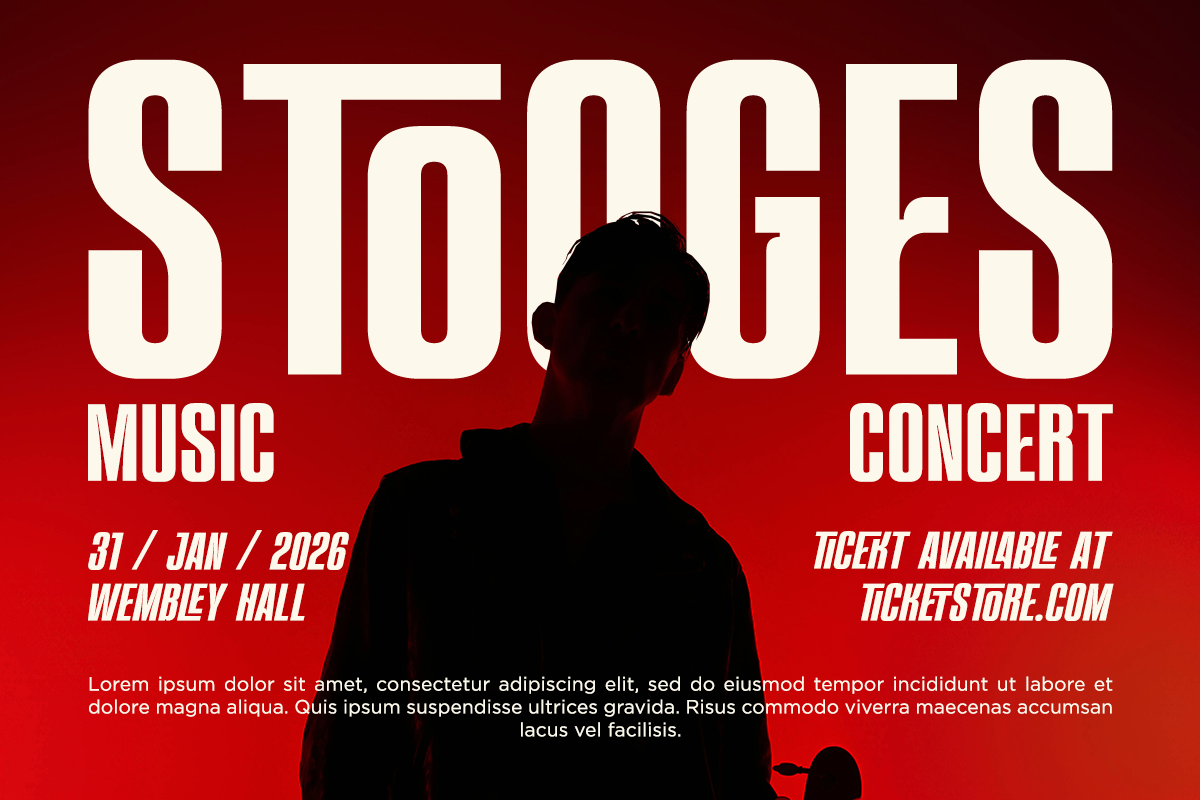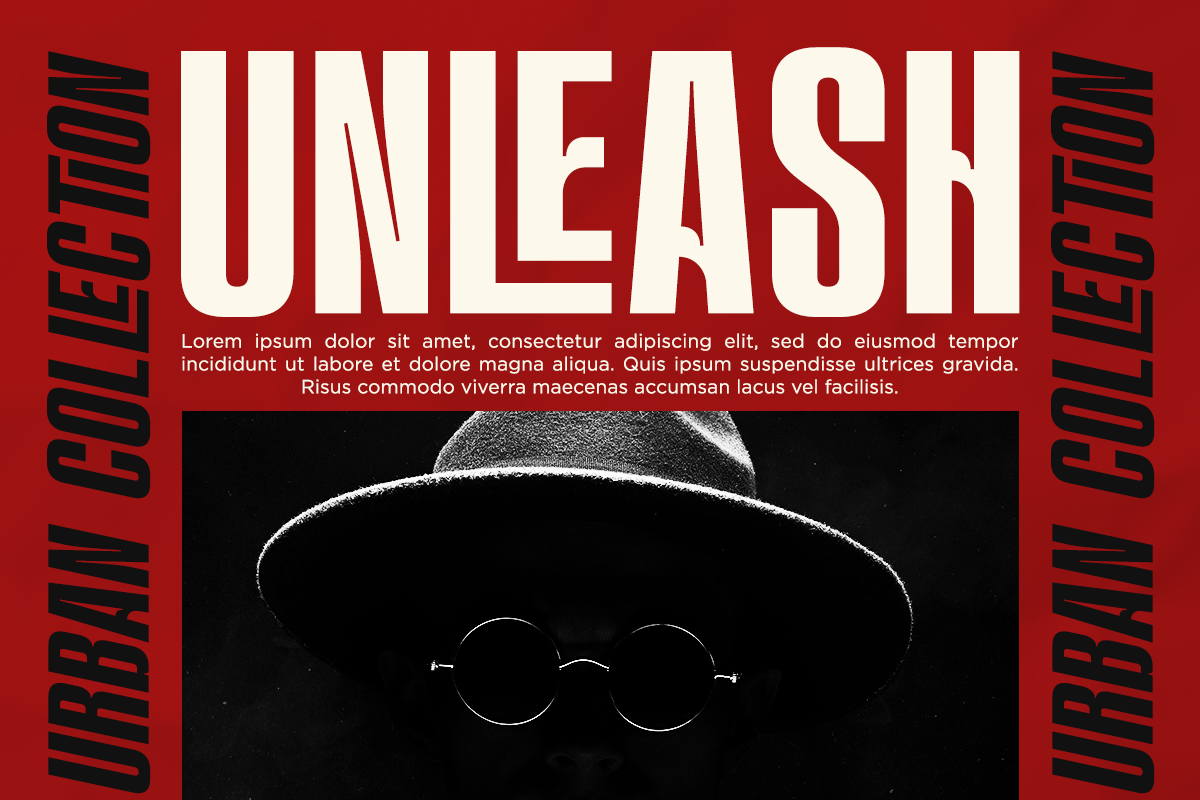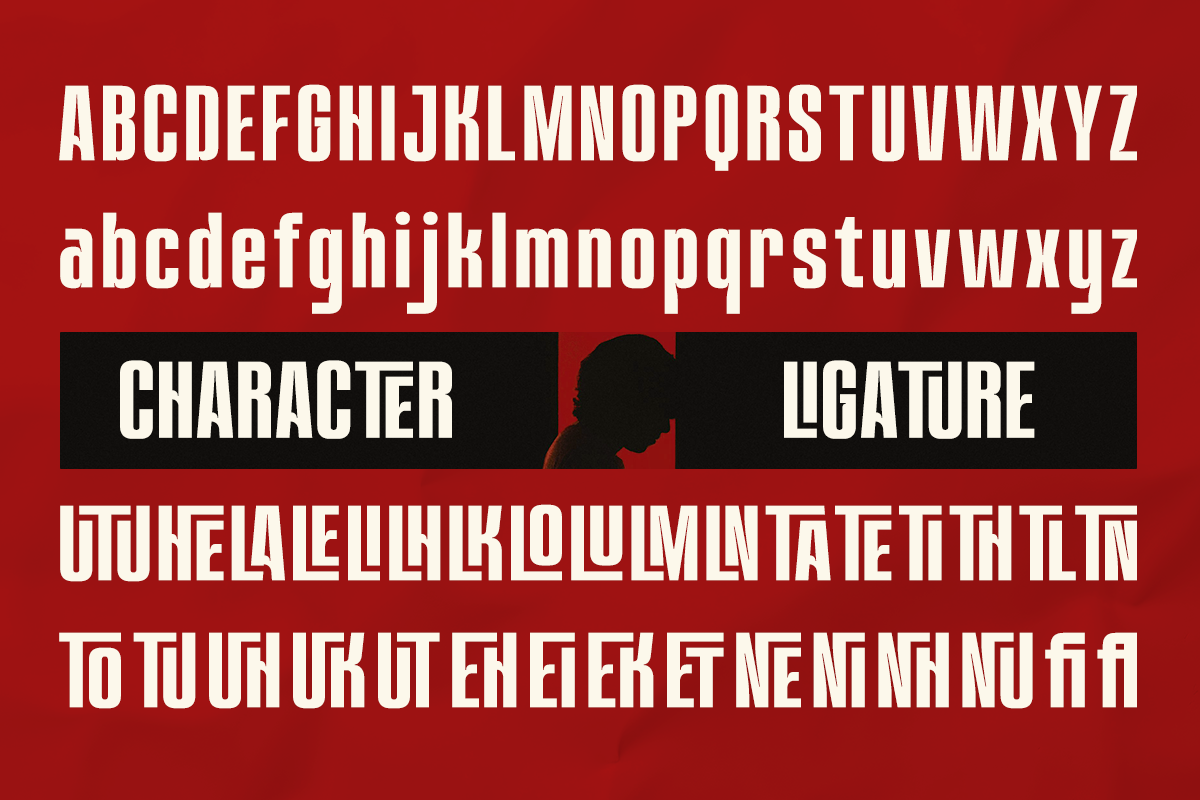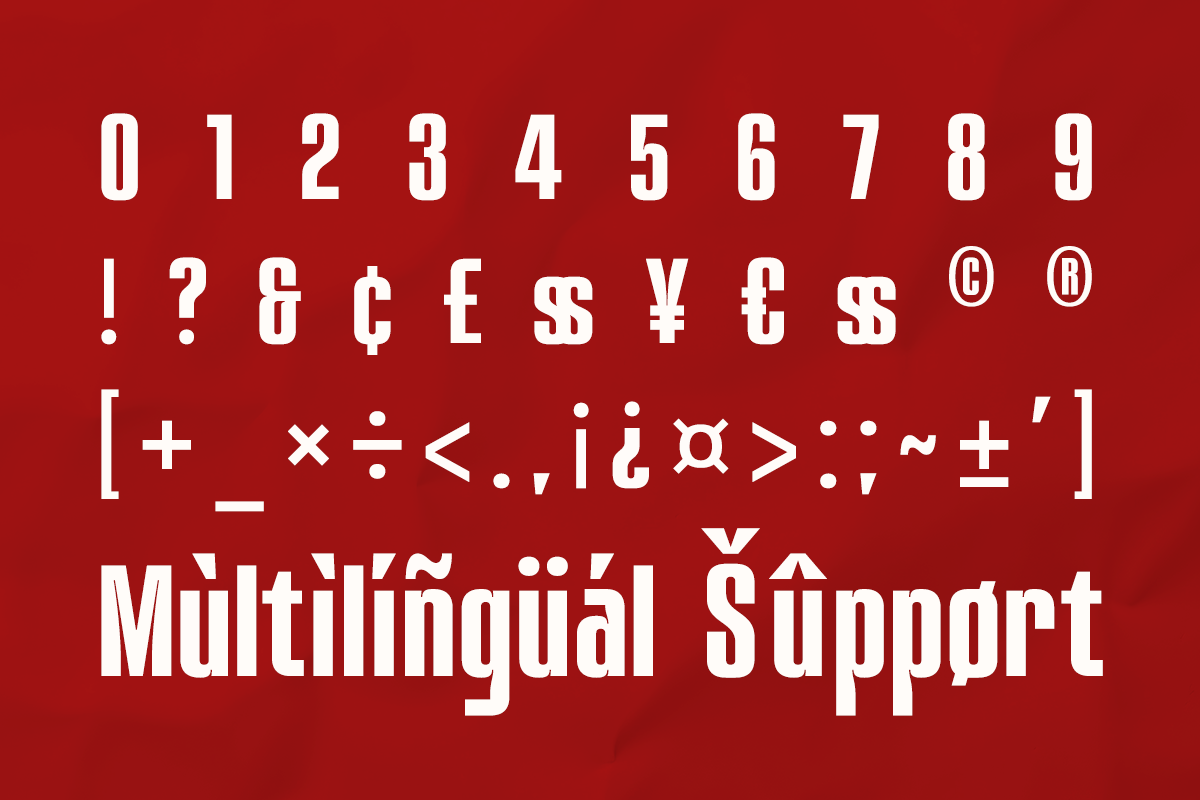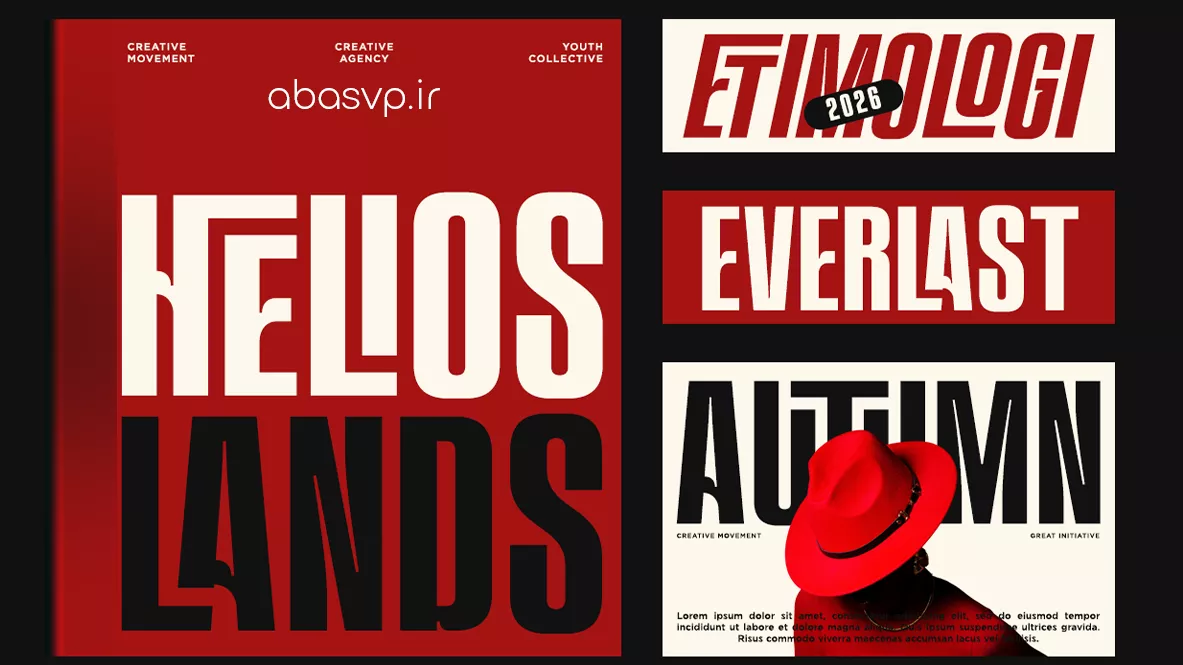
فونت انگلیسی Font Artboard
فونت Font Artboard
این یک سبک فونت انگلیسی گرافیکی است با وزن ضخیم و بولد که می توانید برای طراحی پوستر و بنرهای تبلیغاتی و نیز عنوان های اصلی در کاور های ویدیویی برای تامنیل یوتویب هم استفاده کنید. این فونت انگلیسی جدیدترین فونت 2026 با خطوط و طراحی متفاوتی برای پروژ ه های گرافیک شما است که چندین نمونه هم در عکس ها قرار دادیم.